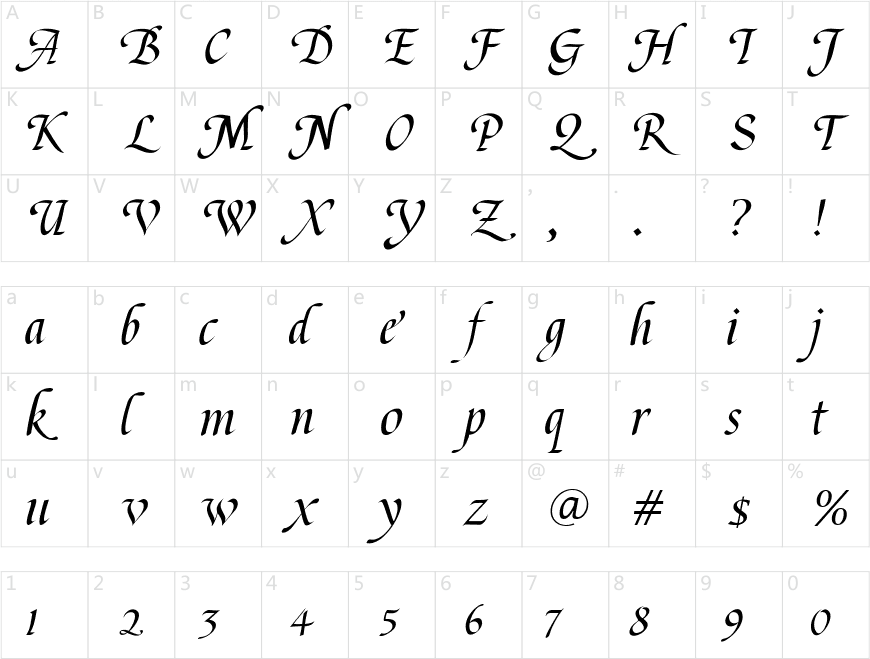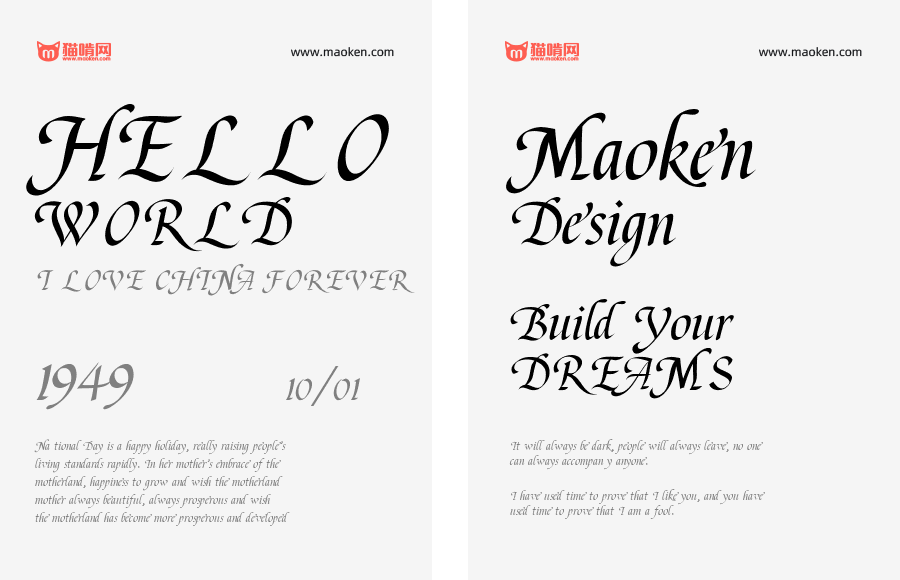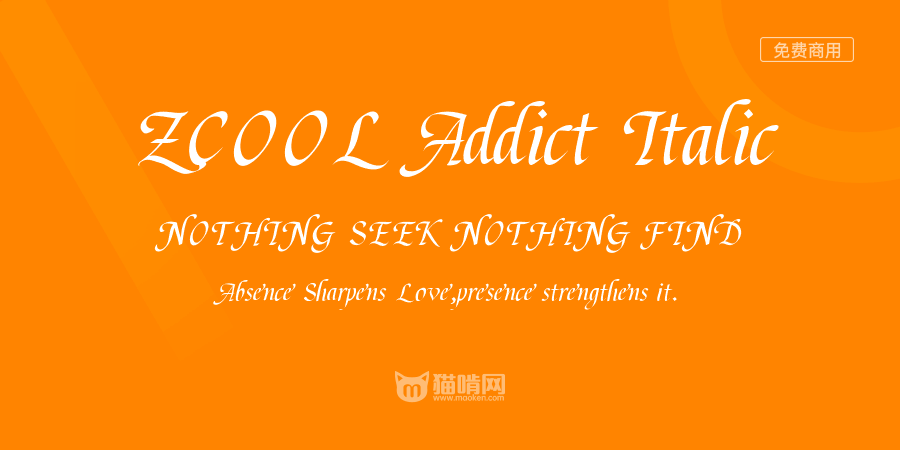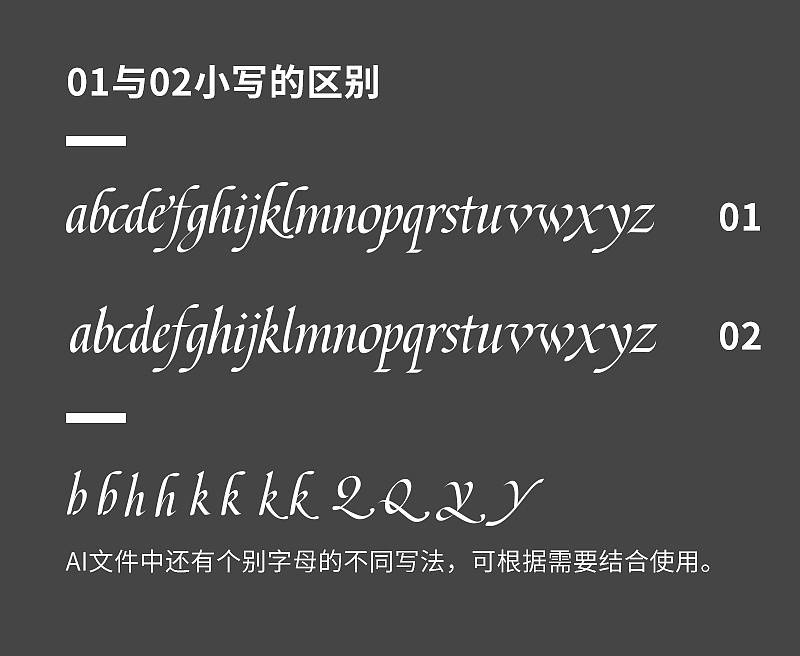
ZCOOL Addict Italic
玩平行笔有一年多了,虽然写的还是不怎么好,但是至少可以见人啦,哈哈。
所以我手写了一套意大利体并做成了字库,部分字母在写法上有所改进。
这套字体创作了一个多月,从草稿到矢量到用FontStudio做成字库TTF安装文件,都是我一个人完成。
01与02的区别主要是小写字母的写法有所不同,具体可以看正文,实际使用中两者可结合使用。
字库字体以站酷ZCOOL冠名原因有二:
1.自从刚大二的时候不小心戳进了站酷这个交流平台,我的进步是飞快的,从大二到现在马上大四的这段时间,已经上了四次首页了,早期关注过我的酷友应该都知道我的成长,所以对站酷和各位帮助过我的酷友和大神,我是很感激的。
2.关注我很久的酷友们都知道,我以前就做过四套英文字库的,都是公益性质的(虽然那些实在有点渣),我希望尽自己的力量对设计这个圈子进一点微薄之力,所以我觉得用站酷冠名会更好一些,如果字体传播很广的话,也可以提高站酷的知名度,作为站酷大家庭的一员,我是希望站酷越办越好的!